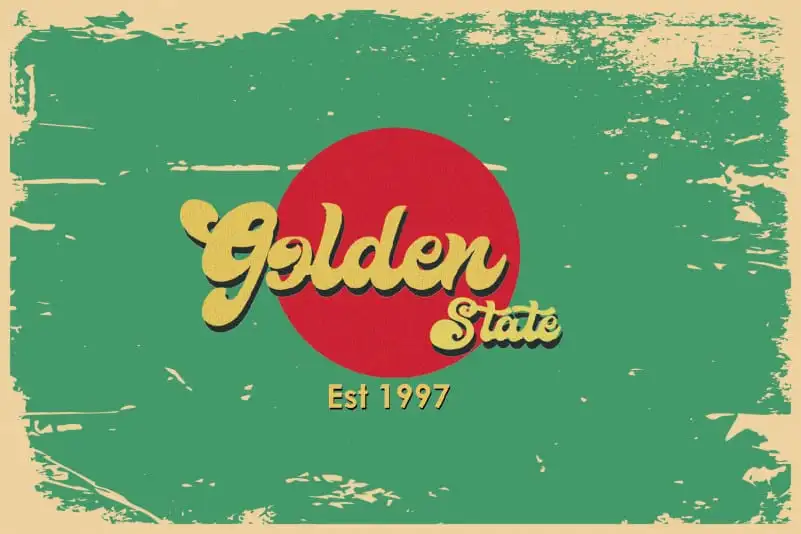
The Retropus Font – Download Grátis
A fonte Retropus é inspirada nos estilos retro e a mistura com letra manuscrita. Foi criada com uma pegada personalizada em cada curva, dando-lhe um toque único que desejo inspire seus trabalhos. Um destaque interessante da fonte é sua linha base muito leve, ideal para texturas levemente onduladas ou estilizadas. Além disso, Retropus inclui uma combinação perfeita de uma fonte complementar e um conjunto de bonus Swash que são extremamente úteis em diversas aplicações, como logotipos, citações escritas a mão, embalagens de produtos, cabeçalhos, outdoors, material promocional e cartões de felicitações. A fonte Retropus é perfeita para várias necessidades do design gráfico moderno, combinando uma personalidade única com funcionalidades práticas e versáteis.